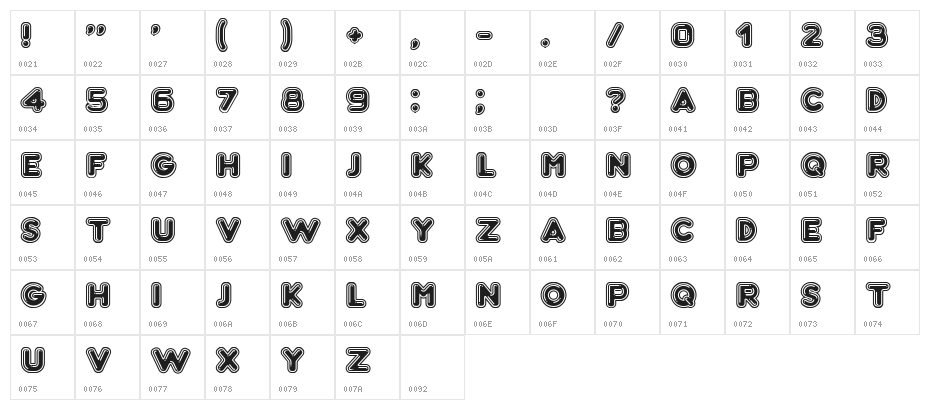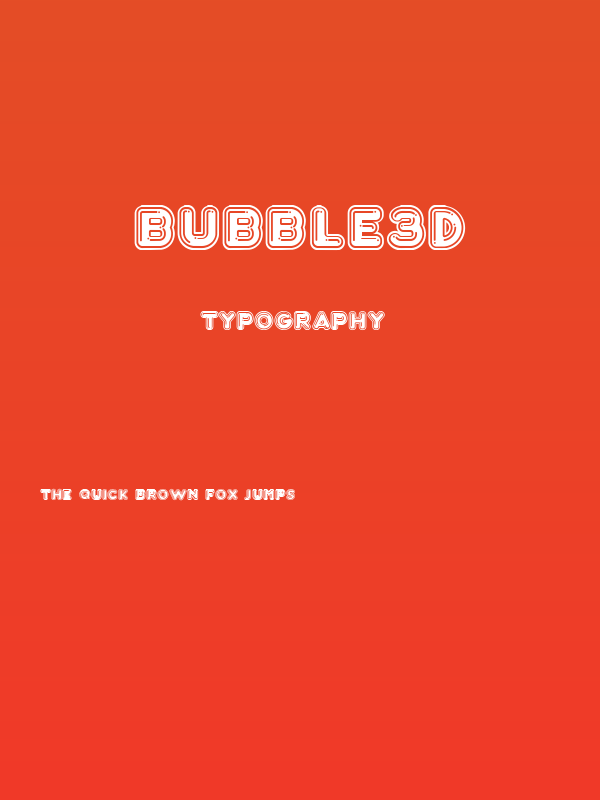
Bubble3D Font
| Gesamtstil | Playful, Modern |
| Vorgeschlagene Projekte | Perfect for children's book covers, playful branding, party invitations, and eye-catching posters. |